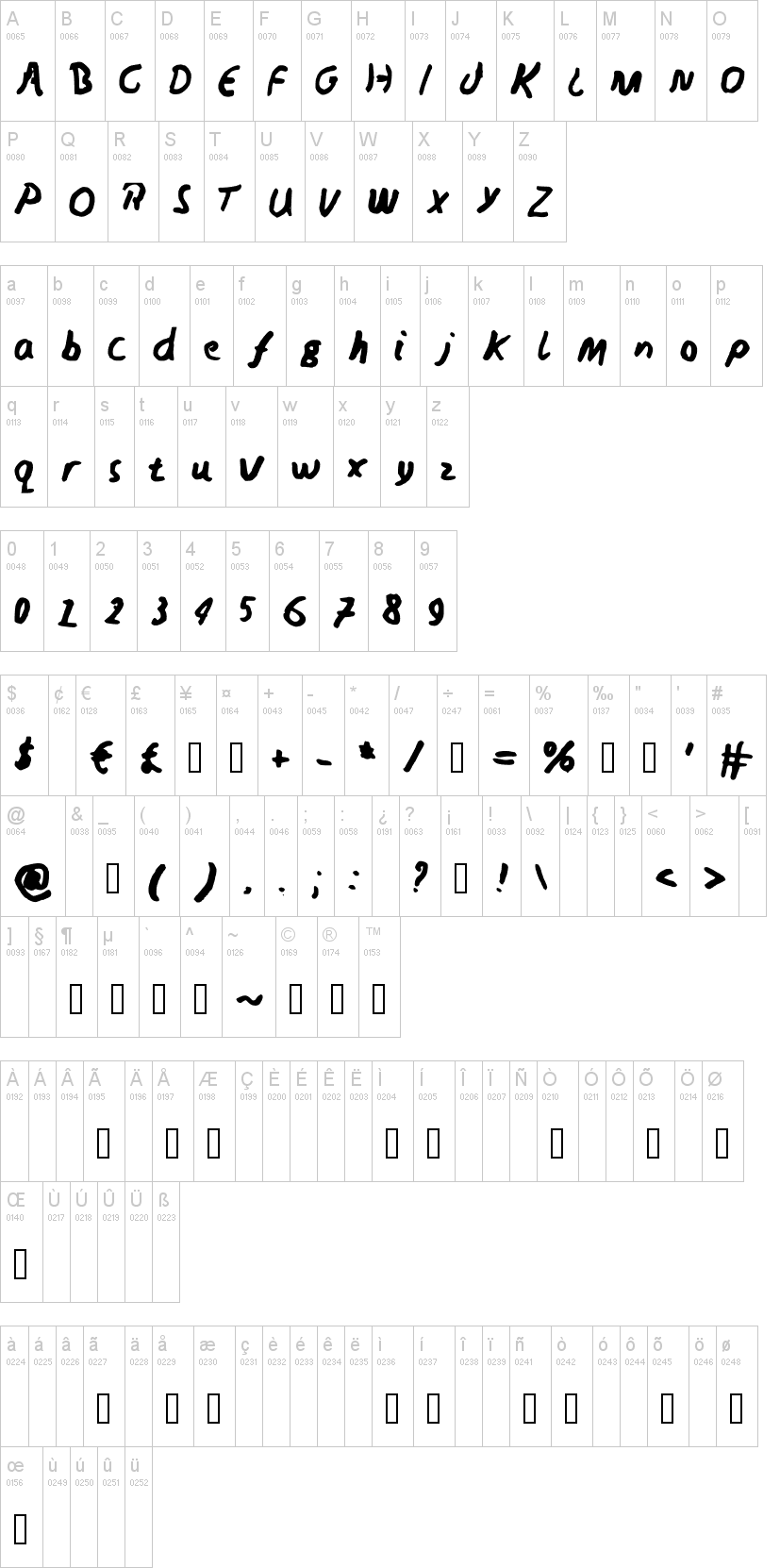
Neds Writing
Neds Writing是一款由Ned Dwyer设计的英文字体,它是一款简洁、大胆、活泼的英文字体,具有清新的感觉,能够大大提升你的文字设计作品的美感。它的主要特点是:字体显示细节丰富,笔画精细,英文字母中的线条多样,更有利于让你的文字设计作品更加活泼。此外,Neds Writing字体具有良好的可读性,能够清晰地传达你的信息,使你的文字设计作品更加有说服力。
Neds Writing是一款非常不错的手写艺术字体,具有很好的视觉感,适合于文化类的宣传设计、商业类品牌的广告和产品包装设计以及个性化文字排版等较多场景。